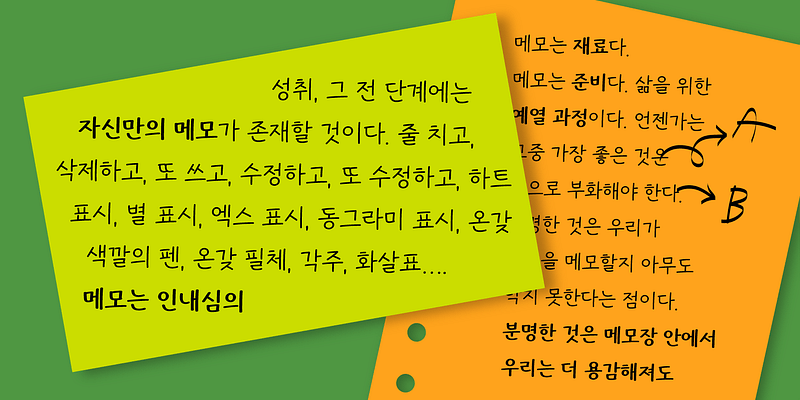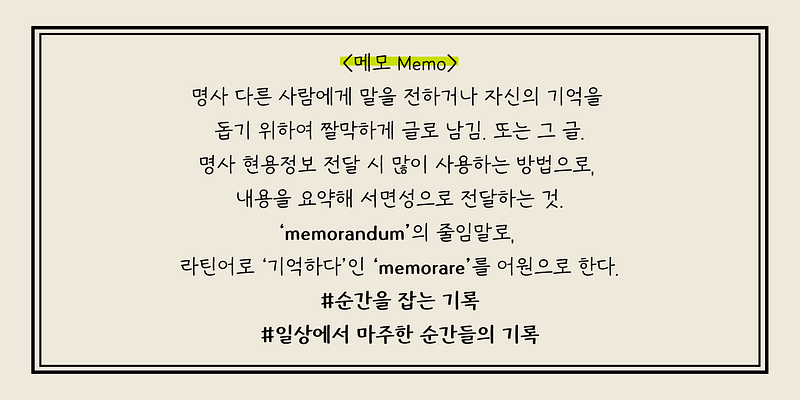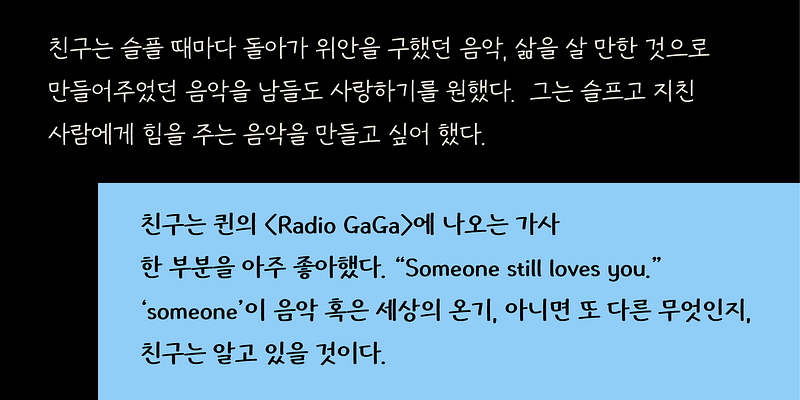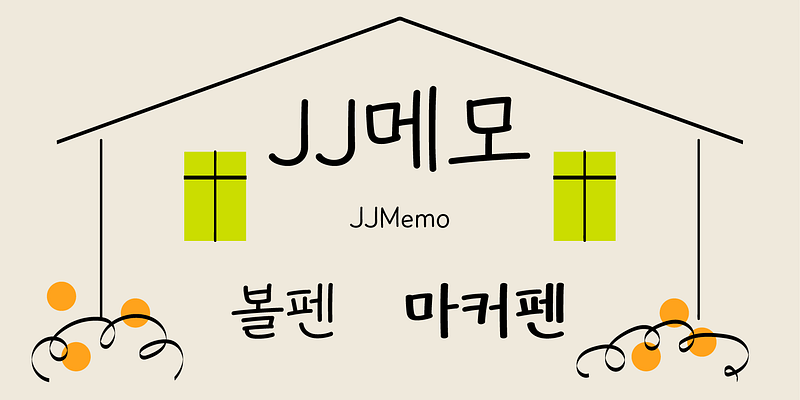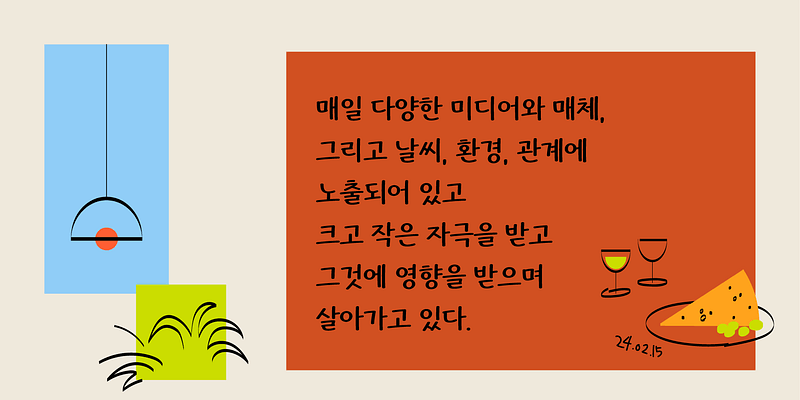
Cada caractere cuidadosamente escrito forma palavras gradualmente, que se unem na criação de frases e parágrafos. Essa fonte foi inspirada na crença de que inclusive as menores anotações diárias podem ser concentradas e criar pequenos milagres. A oferece uma impressão confortável, acessível e organizada em qualquer dispositivo, sem causar estresse visual. Ela está disponível em duas espessuras, adaptadas para atender a diferentes ferramentas.